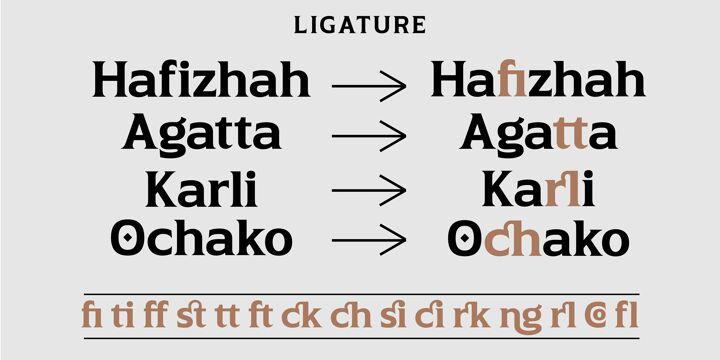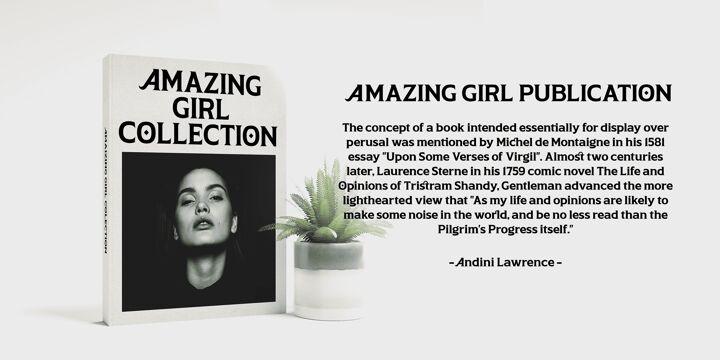
Aliey Font
Description de Aliey Font
Aliey est une police victorienne élégante et audacieuse qui semble incroyable dans les grands comme dans les petits environnements. Idéalement utilisé comme présentoir pour les titres et les logos, les lignes droites, les courbes tendues et les arêtes vives d’Aliey donnent à tout projet une touche de classe supplémentaire. Cette police serif vintage est stable et confiante, et amène les pensées à une époque d’or et de marbre.
La famille Aliey se compose de quatre styles : les deux graisses Regular et Bold, chacune en italique. La police est construite avec la fonctionnalité OpenType avancée et offre une qualité garantie de premier ordre, contenant des alternatives stylistiques et contextuelles, des ligatures et plus de fonctionnalités ; tout cela pour vous donner un contrôle total et une personnalisation. Il dispose d’un support linguistique étendu, couvrant toutes les langues latines, de l’Europe du Nord à l’Afrique du Sud, de l’Amérique à l’Asie du Sud-Est. Il contient tous les caractères et symboles dont vous aurez besoin, y compris tous les signes de ponctuation et tous les chiffres.